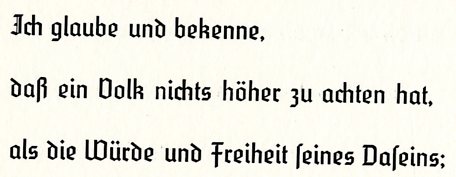
Benötige Hilfe bei der Identifizierung einer Schrift
ich habe hier ein Buch vorliegen (handgebunden auf 30 Exemplare limitiert, von privat auf zwei Holzdeckeln gezogen) mit den Bekenntnissen von Clausewitz. Mich interessiert vor allem die verwendete Schriftart. Vielleicht kann mir hier jemand helfen.
Das müsste die Element von Max Bittrof sein
Vielen Dank. Kommt nahe heran, aber unterscheidet sich zum Beispiel im großen "i". Möglicherweise lediglich eine Abwandlung der Element.
Ich hab hier ein Muster der Element gefunden:
Das I in deinem Beispiel scheint eine Abwandlung zu sein oder einem anderen Font zu entspringen.
Gab es in der Tat.